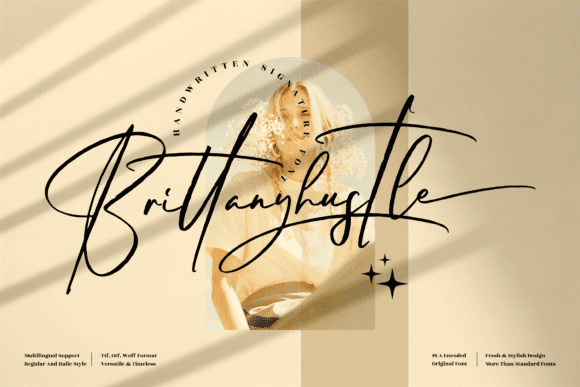
Название: Brittanyhustle Font (2021)
Brittanyhustle - это модный и нежный рукописный шрифт.
Изящный и стильный, этот шрифт идеально подойдет для написания свадебных приглашений, открыток или любого другого дизайна, которому может понадобиться романтический, персонализированный штрих!